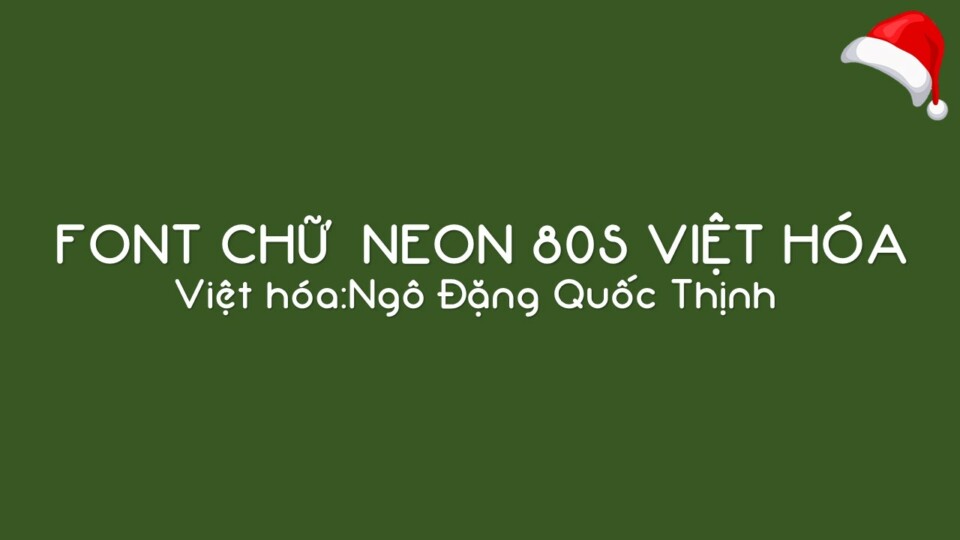
Font việt hóa Neon 80s: Mang phong cách cổ điển vào thiết kế hiện đại
Giới thiệu về Font việt hóa Neon 80s trong thiết kế đồ họa
Trong thế giới sáng tạo, việc lựa chọn Font Chữ phù hợp đóng vai trò quyết định đến linh hồn của tác phẩm. Font việt hóa Neon 80s là một bộ phông đặc biệt, tái hiện hoàn hảo ánh đèn neon rực rỡ từ những thập niên cũ. Đối với các bạn học sinh và giáo viên, việc sử dụng bộ font này không chỉ giúp bài thuyết trình thêm sinh động mà còn khơi gợi cảm hứng về một thời kỳ nghệ thuật đầy ấn tượng. Nhờ được tối ưu hóa tiếng Việt, người dùng có thể dễ dàng soạn thảo văn bản mà không lo lỗi hiển thị hay thiếu dấu.
Đặc điểm nổi bật và ứng dụng của Font việt hóa Neon 80s
Phong cách hoài cổ kết hợp tính hiện đại
Font việt hóa Neon 80s sở hữu những đường nét mảnh mai nhưng sắc sảo, mô phỏng chân thực các ống đèn uốn lượn tại các biển hiệu quảng cáo xưa. Điểm mạnh của bộ font này là khả năng tạo ra hiệu ứng thị giác mạnh mẽ, đặc biệt khi kết hợp với các hiệu ứng đổ bóng hoặc phát sáng trong các phần mềm thiết kế. Đây là lựa chọn lý tưởng cho các poster sự kiện trường học hoặc bìa báo tường mang phong cách Retro.
Tính ứng dụng cao trong môi trường giáo dục
Không chỉ dùng cho mục đích giải trí, bộ font này còn giúp các bài giảng điện tử trở nên lôi cuốn hơn. Giáo viên có thể dùng nó để làm nổi bật các tiêu đề chính, giúp học sinh dễ dàng ghi nhớ nội dung bài học thông qua hình ảnh trực quan sinh động.
Kết luận về bộ Font việt hóa Neon 80s miễn phí
Việc sở hữu Font việt hóa Neon 80s sẽ giúp bạn mở rộng tư duy sáng tạo và làm mới các sản phẩm thiết kế cá nhân. Đây là một công cụ hỗ trợ đắc lực cho những ai yêu thích vẻ đẹp cổ điển của những năm 1980. Nếu bạn đang tìm kiếm một bộ Font Miễn Phí, Font Việt Hóa, Font việt hóa Neon 80s chất lượng để phục vụ học tập và làm việc, hãy trải nghiệm ngay để thấy sự khác biệt trong từng nét chữ Việt.